OnePlus透露了其新徽标,该徽标的特征是曲线形的“ 1”,较大的“ +”(该公司表示对社区表示敬意)和更突出,更清洁的“ oneplus”。
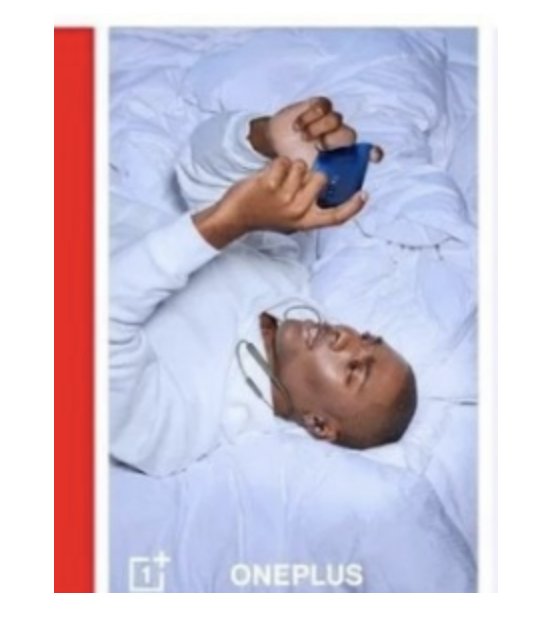
作为其新视觉标识的一部分,OnePlus还引入了一种新字体,该字体“可提高可读性,并且在眼睛上更容易使用”。OnePlus尚未共享字体名称,或确认它将在Oxygen OS中使用。
OnePlus还正在扩展其调色板,以使用次要的青色,绿色,洋红色,靛蓝和黄色补充可识别的红色。
新的视觉识别和设计已经进行了七个月。